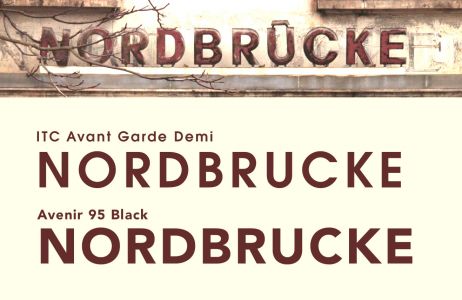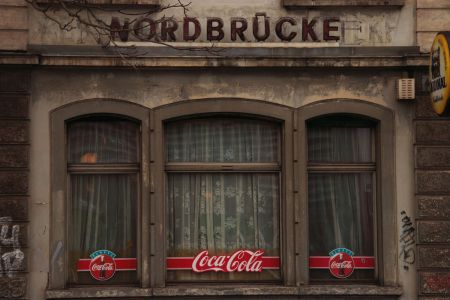
... etwas zu dieser schrift. (NORDBRÜCKE)
Avant Garde ist es nicht, auch Avenir: fehlanzeige. Ich bin ratlos ...
Franklin Gothic passt in etwa, bis auf das C.
... "was in Richtung" ...
Die Originalschrift der "gebauten" Buchstaben wirste eh nicht finden.
... "was in Richtung" ...
Die Originalschrift der "gebauten" Buchstaben wirste eh nicht finden.
... das befürcht ich eben auch.
nun ja. wie oberhalb bereits erwähnt, ich denke nicht,
dass ich eine schrift finden werde die genau dieser
vorgabe entspricht.
Das schmale "D" tanzt optisch sowieso aus der reihe.
sieht aus wie ein verirrter "condensed"-schnitt ... :)
meiner meinung kommt die avant garde am ehesten an
die vorlage heran. auch wenn sie in meinem beispiel ein
wenig zu leicht wirkt.
für die erstellung der neuen beschriftung (restaurant)
werde ich wohl trotzdem auf frutigers, wunderschöne,
avenir zurückgreifen.